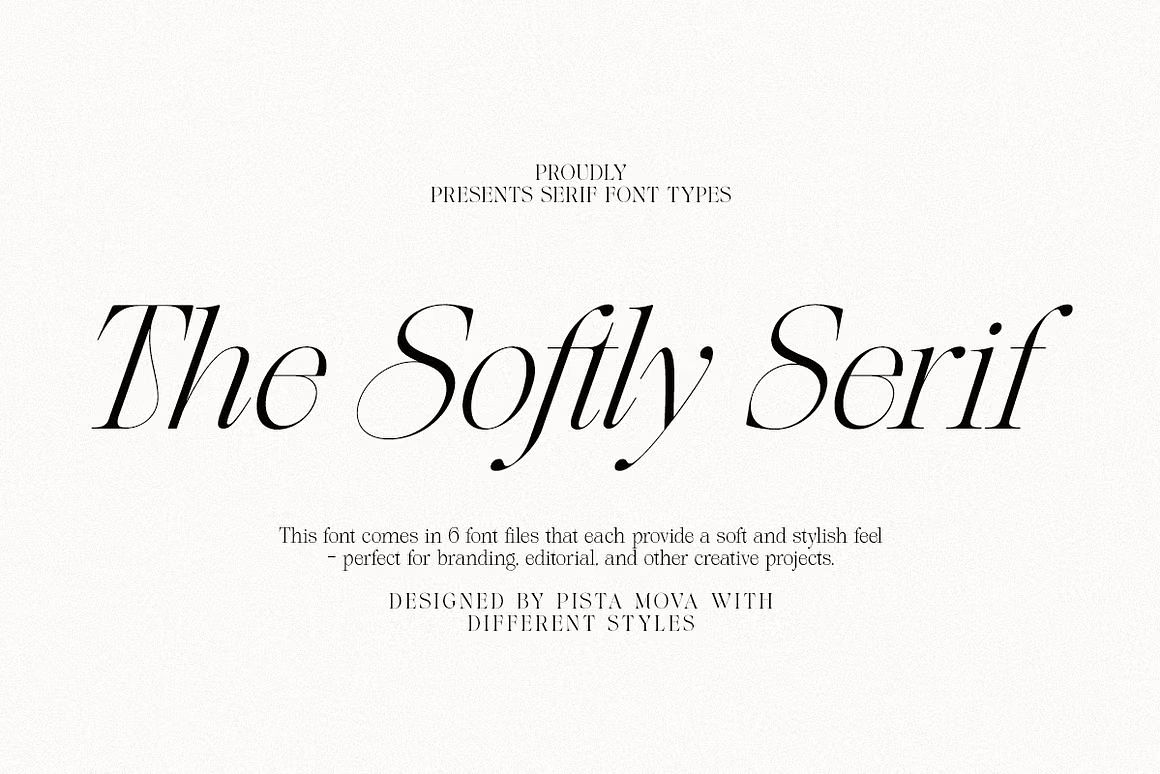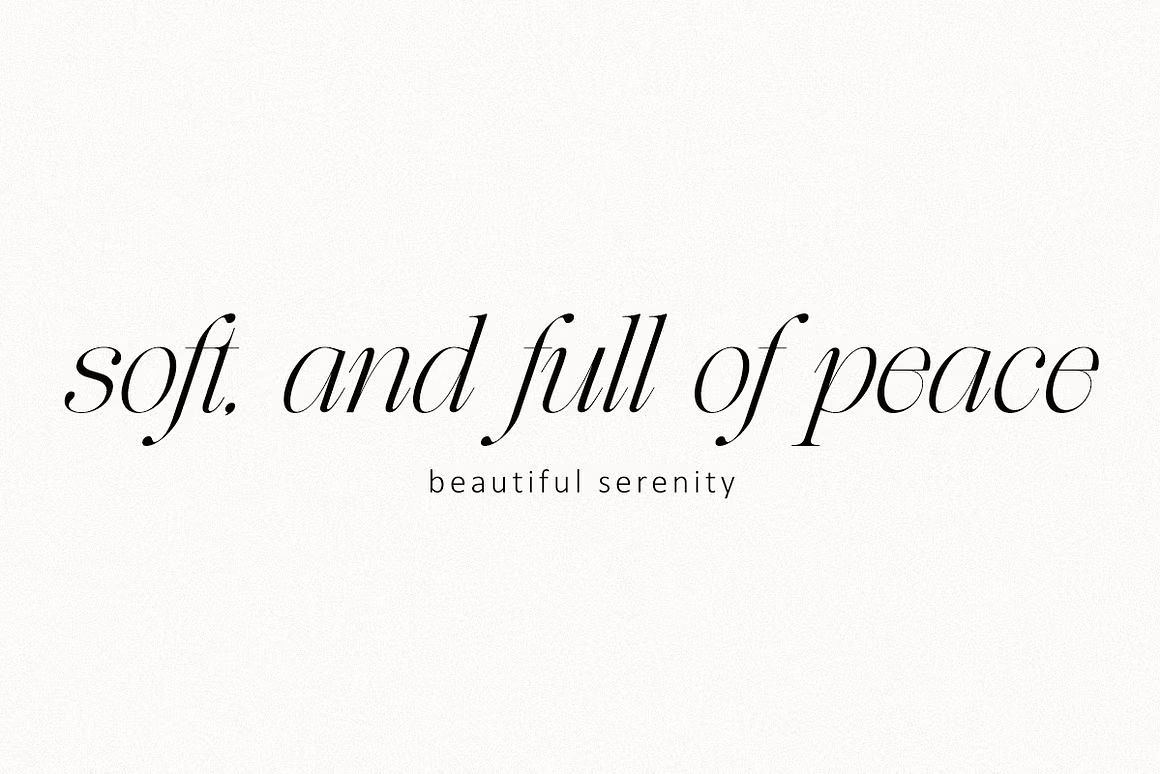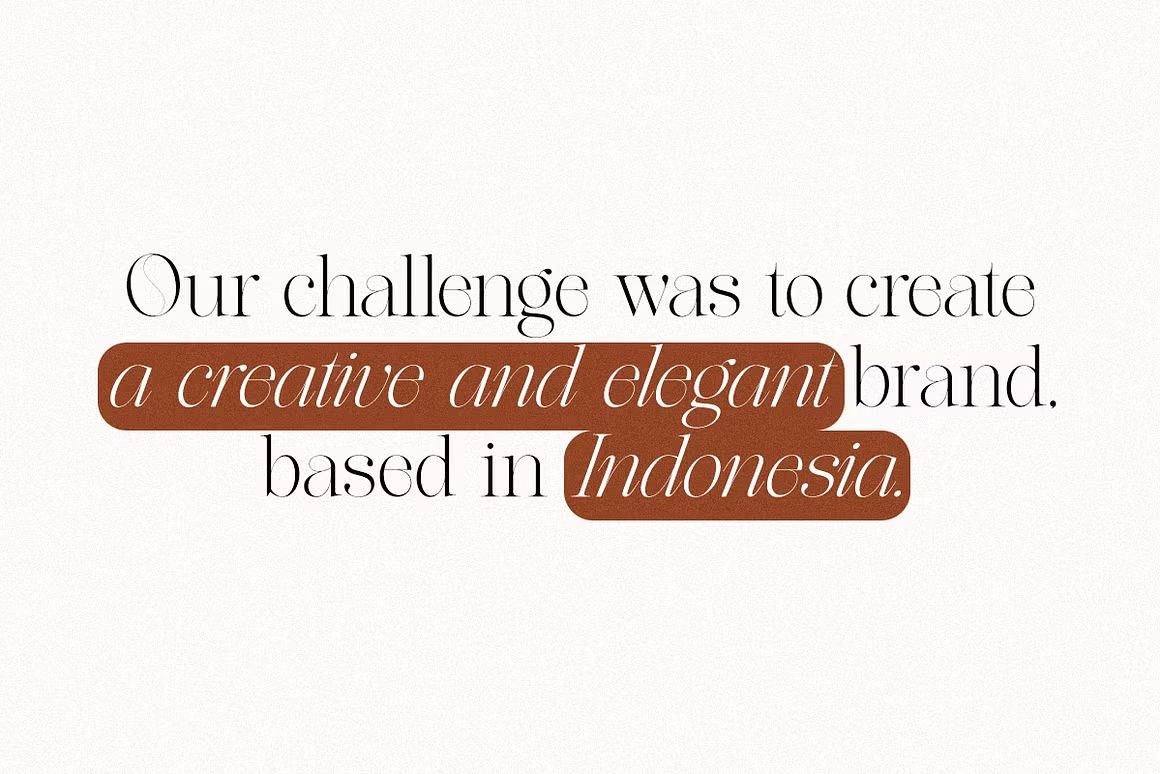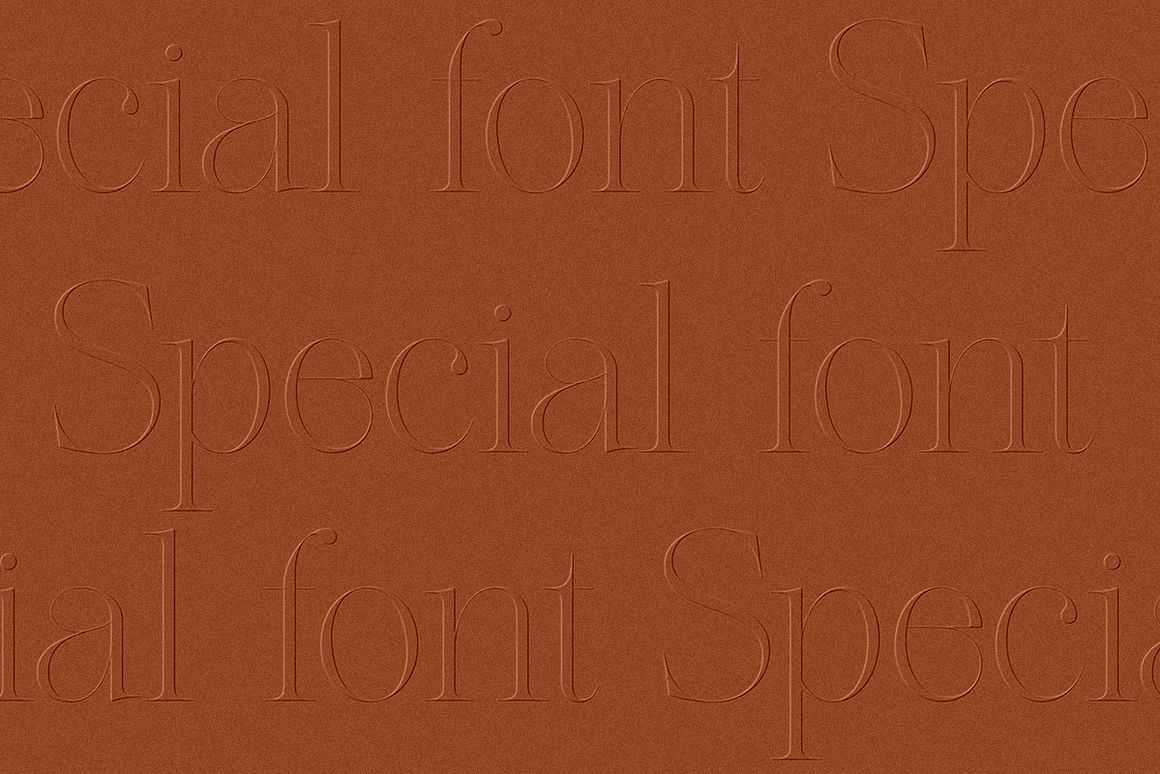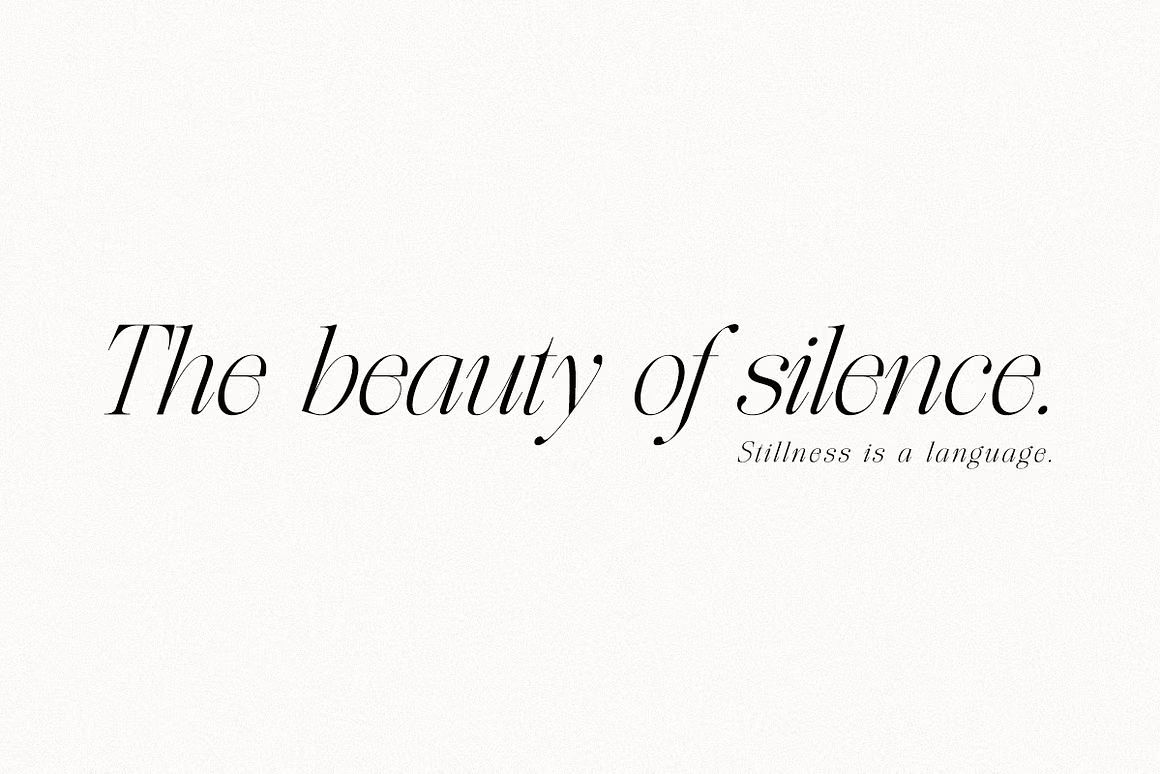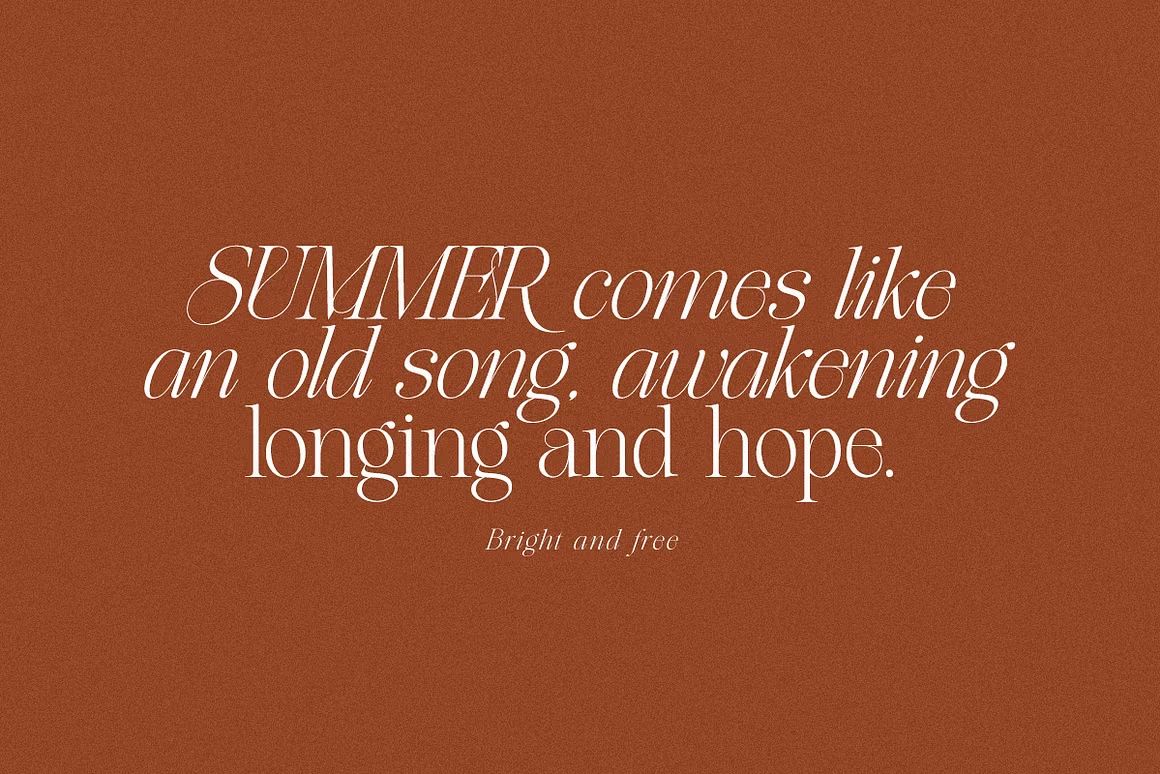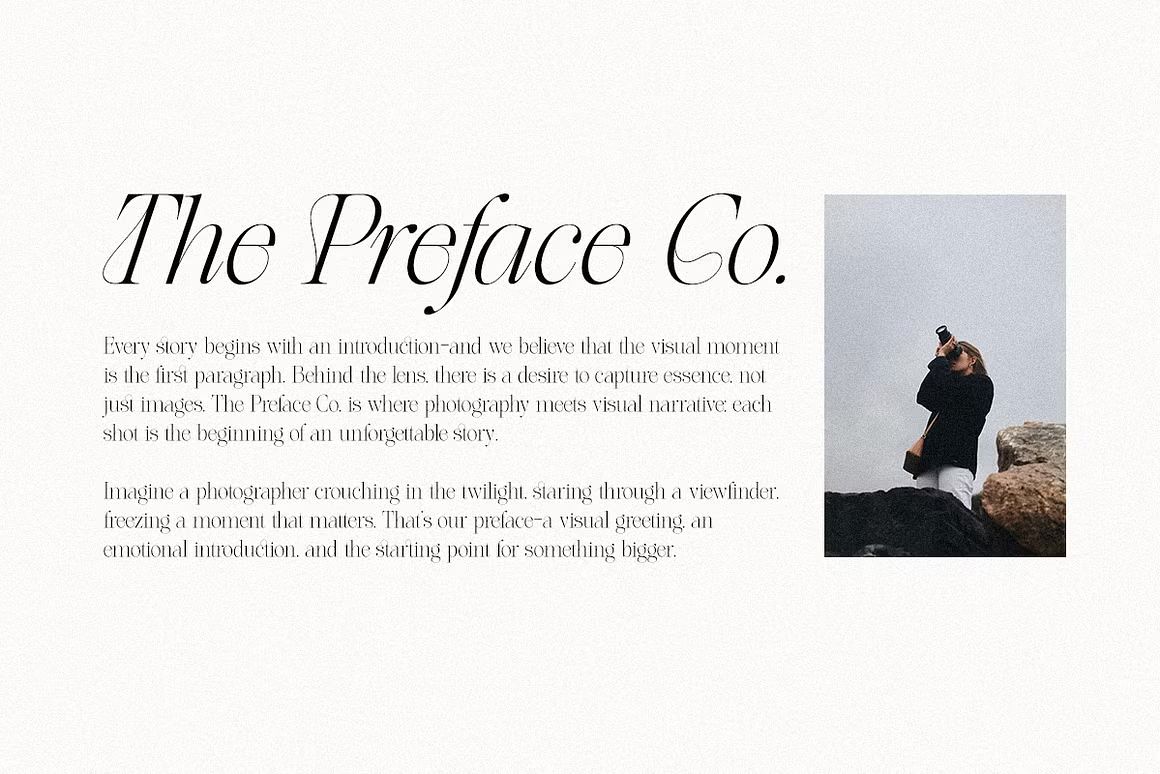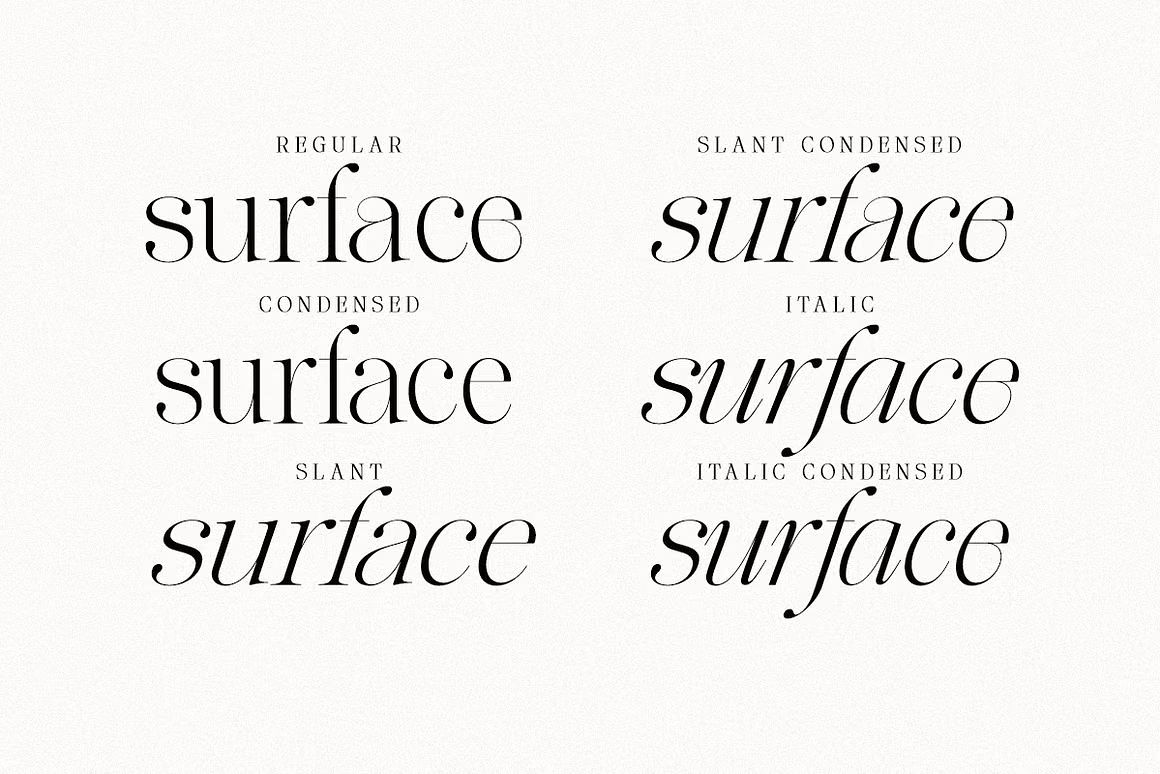
The Softly – Serif Font
The Softly adalah font serif dengan tampilan lembut dan elegan, sempurna untuk desain branding, editorial, undangan, dan proyek kreatif yang mengutamakan kesan klasik dan feminin.
The Softly adalah font serif dengan karakter halus dan elegan, dirancang untuk memberikan sentuhan klasik namun tetap modern pada setiap desain. Cocok digunakan untuk branding, editorial, undangan, logo, dan proyek visual lainnya yang membutuhkan nuansa anggun dan profesional. Garis lembut dan bentuk huruf yang seimbang menjadikan The Softly pilihan ideal untuk tampilan yang berkelas dan feminin.
Fitur unggulan:
• Gaya serif lembut dengan sentuhan elegan dan modern
• Cocok untuk branding, editorial, undangan, dan logo
• Termasuk huruf besar, huruf kecil, angka, dan simbol
• Ideal untuk proyek cetak maupun digital yang berkesan mewah